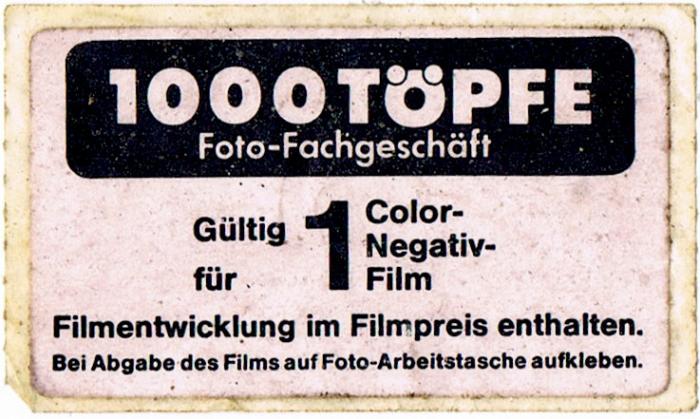
Das ist – zumindest die Unterzeile – sehr dicht an der Futura Extra bold dran. Das »1000 Töpfe« sieht eigenwillig aus. Ich könnte mir vorstellen, dass da eine Satzschrift von Hand so verändert wurde.
Ich könnte mir gut vorstellen, dass es nie eine Satzschrift war, sondern das Werk eines Grafikers. 1000Töpfe ist ja eine sehr frühe Nachkriegsgründung gewesen, und, so lange ich mich an diesen Laden erinnere (besonders diesen fürchterlich wuseligen Laden, bestehend aud zusammengewüfelten Ruinen-Erdgeschoß-Resten, dazwischen gebauten Flachdach-Behelfskonstrumtien und dann wieder durch unzerstörte Wohnhäuser am Ende der Langen Reihe in StGeorg, und dieses fast schon schleimpilz artige Wabern mit über jeweils recht kurze Zeiträume zusätzlich angemietete Flächen rund herum. Eine Zeit lang hatten die da ein richtig tollen Profi-Fotoshop in der Schmilinskystraße, noch ein stüch weiter Richtung Alster...
Tja, und so lange ich die kannte, sah das Logo eigentlich immer recht gleich aus (dieses letzte scheint aber nicht ganz original zu sein, die 1 ist falsch, und dieser Bimdestrich?)
Ich habe noch einen Entwicklungs-Gutschein aus den frühen 1980er Jahren - Hmm, jetzt bekomme ich damit keinen Film mehr entwickelt :-(
(im Original ist der nicht so ausgebleicht, sondern so ein Feuerwehrauto-Leuchtrot, das mein Scanner wohl durcheinander bringt, statt der TT-Standard Hausfarbe Gelb Schwarz.